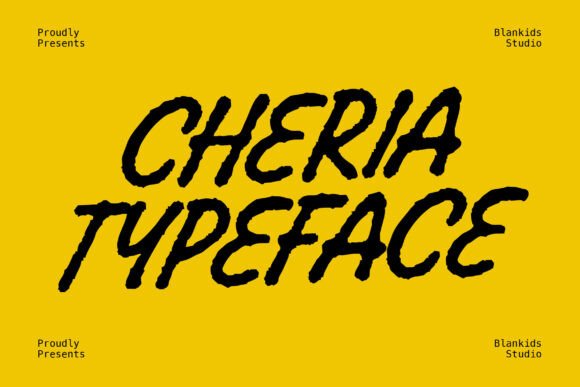
Cheria Typeface
การค้นหาองค์ประกอบการออกแบบที่เหมาะสมอาจเป็นเรื่องท้าทาย แต่ Cheria Typeface นำเสนอคอลเลกชันที่โดดเด่นซึ่งช่วยยกระดับงานของคุณได้ทันที
สร้างขึ้นอย่างแม่นยำ Cheria Typeface ให้เวกเตอร์ที่สะอาด พิมพ์ตัวอักษรที่ราบรื่น และใบอนุญาตเชิงพาณิชย์เพื่อความสบายใจ
ไม่ว่าคุณจะสร้างผลิตภัณฑ์ POD (Print on Demand) คำเชิญงานแต่งงาน หรือกราฟิกโซเชียลมีเดีย Cheria Typeface ก็เหมาะสมอย่างยิ่ง
เคล็ดลับจากผู้เชี่ยวชาญ: รวมองค์ประกอบเหล่านี้กับฟอนต์เสริมเพื่อสร้างการออกแบบที่โดดเด่นและเป็นเอกลักษณ์